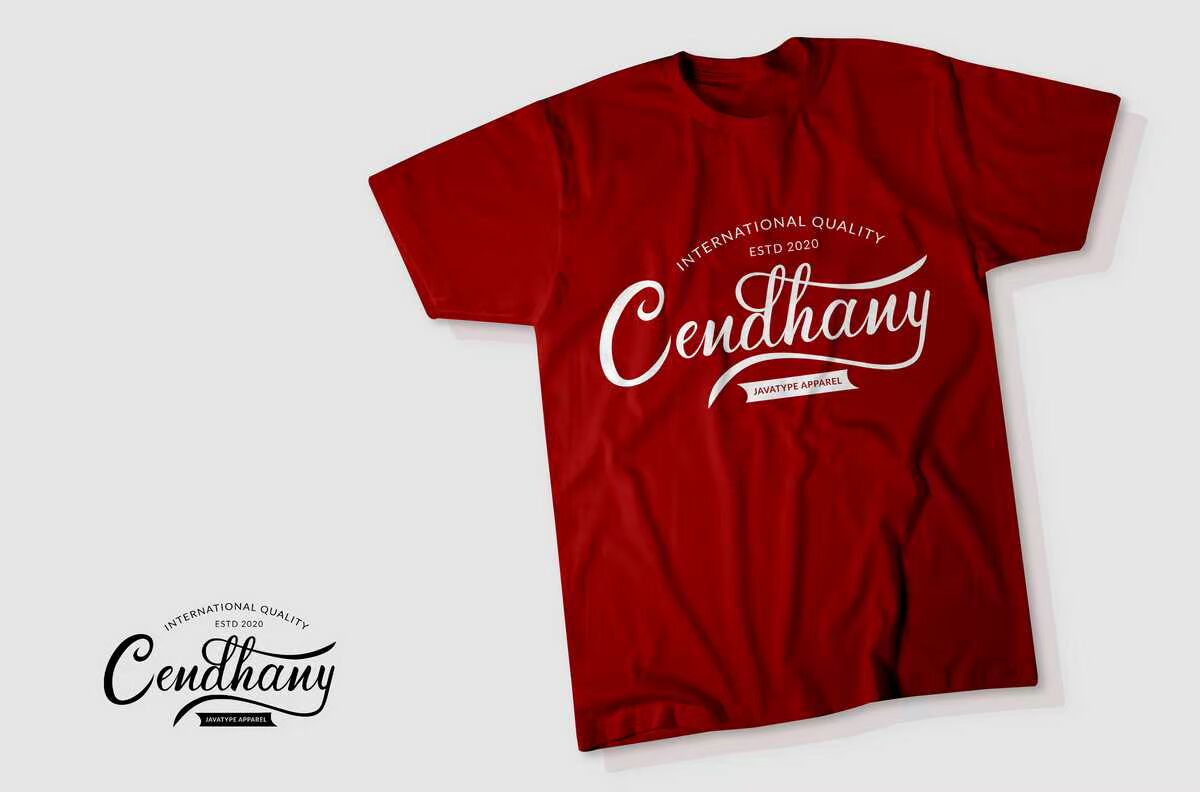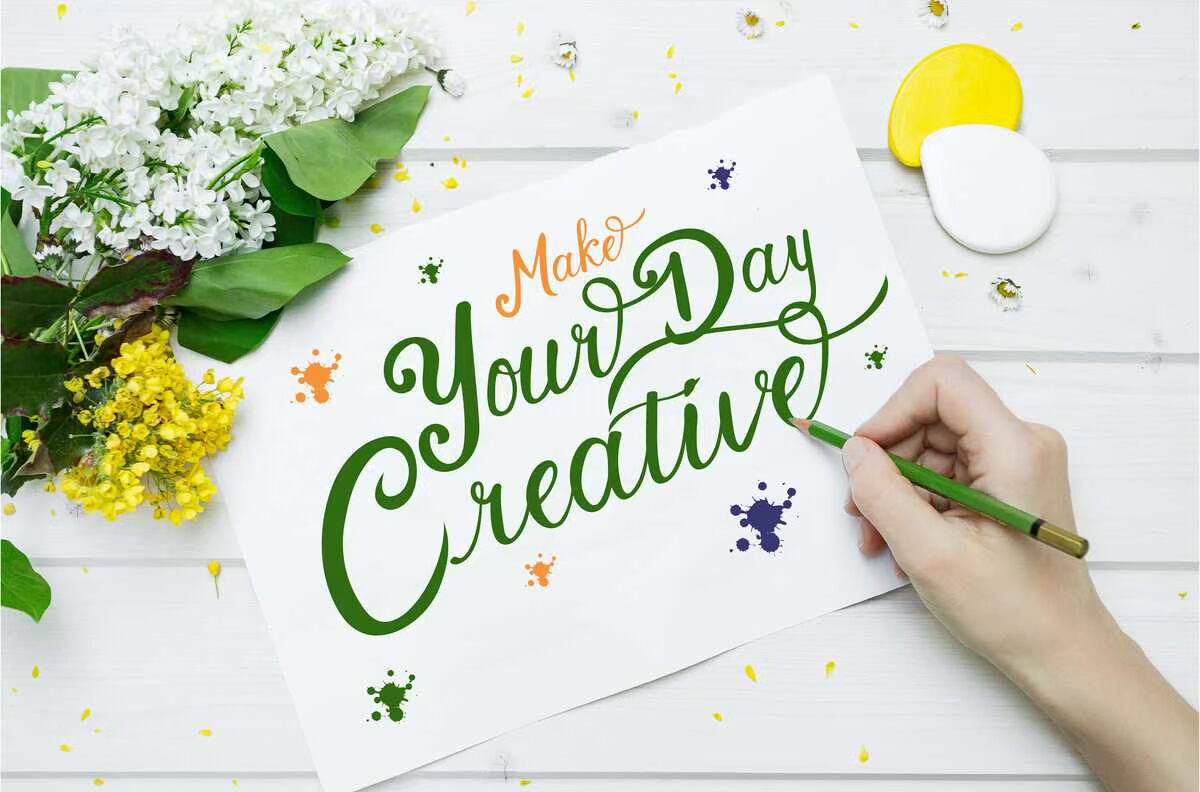
简介汉字和字母字体。这种字体是用刷子自然手写的,因此可以产生高质量的字体。它们非常适合需要字体的人,如标题、标识、服装、邀请、品牌、包装、婚礼、广告等。这种字体有大写、小写、标点、符号、数字、替代、连字、,ETCAL支持多语种。介绍汉字和字母字体。这种字体是由手写的,通常是用刷子书写的,因此可以产生高质量的字体。它们非常适合需要字体的人,如标题、标识、服装、邀请、品牌、包装、婚礼、广告等。这种字体有大小写、标点、符号、数字,交替、连字等支持多语言。